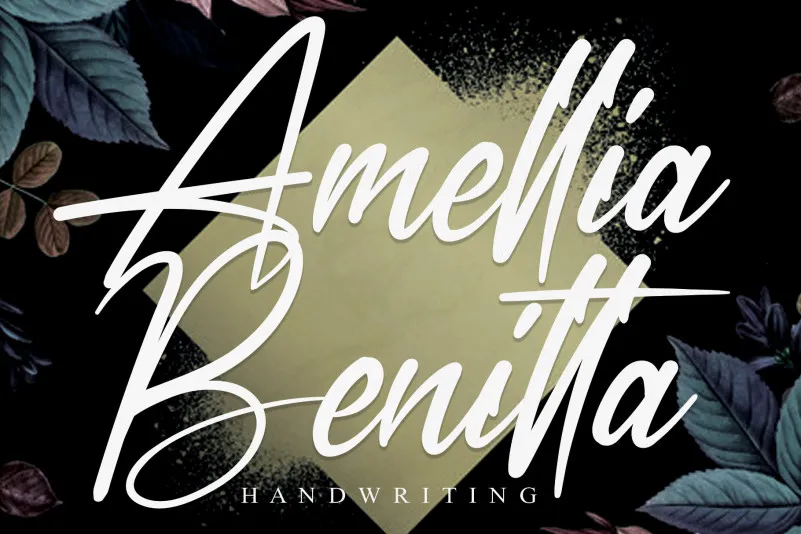
Amellia Benitta Script Font – Download Grátis
Sente-se aconchegado neste ambiente onde o tempo parece se desenrolar lentamente. É uma sensação que a Amellia Benitta Script Font transmite, com suas traços delicados e fluidos. Nesta categoria de fontes escritas à mão, criada pelo designer creativeletter, cada letra é um mimo para os olhos. Seu charme vai além da simples beleza visual; ele se instala em seu design digital, trazendo vida aos textos e batendo palmas ao encorajá-lo a explorar ainda mais as possibilidades criativas. Com Amellia Benitta Script Font você pode dar uma nova vida à sua identidade visual, seja num site profissional ou num relatório de trabalho que expressa nuances sutis. Sua elegância e suavidade são como um braço aberto, esperando recebê-lo para explorar os infinitos possíveis com seu design. Na verdade, é exatamente isso o que a Amellia Benitta Script Font oferece: uma experiência extraordinária em cada caractere. Sem dúvida, ela torna suas criações únicas e memoráveis, fazendo delas algo mais do que apenas texto; são lembranças escritas em letras vivas.